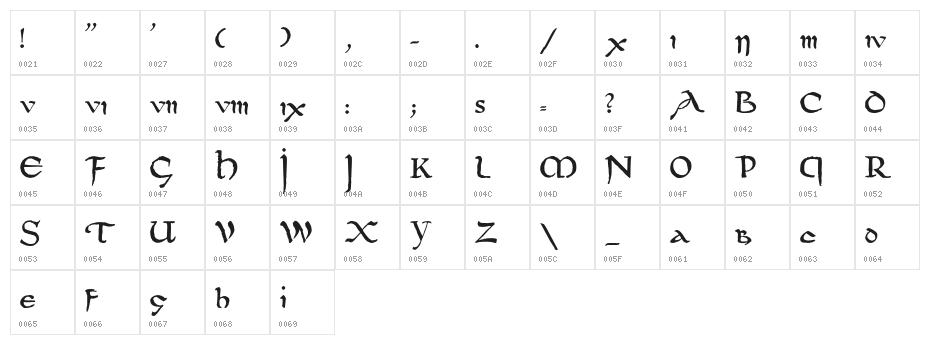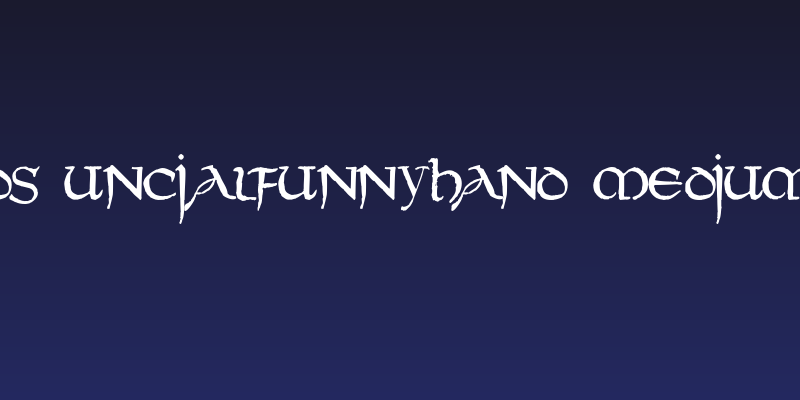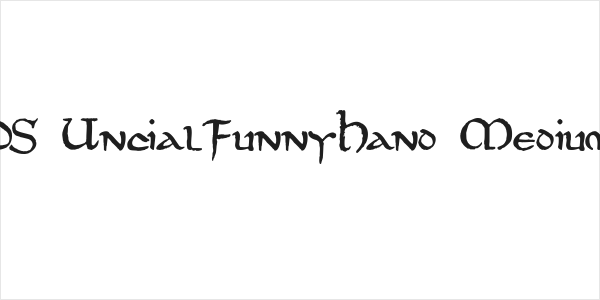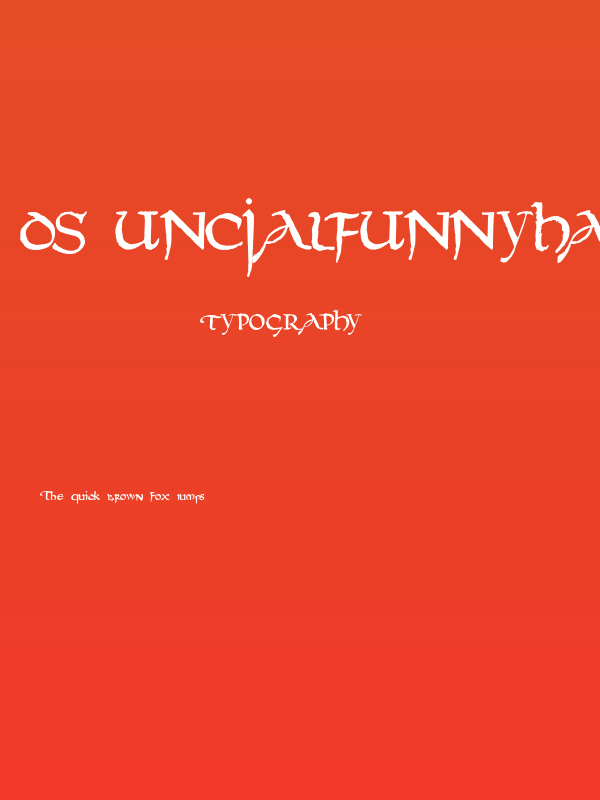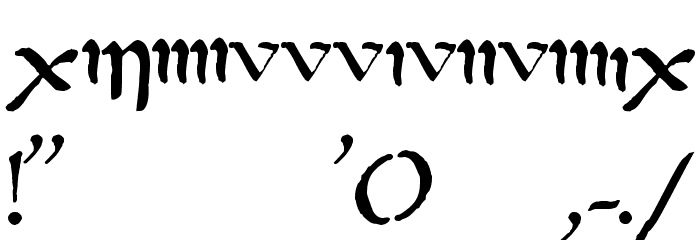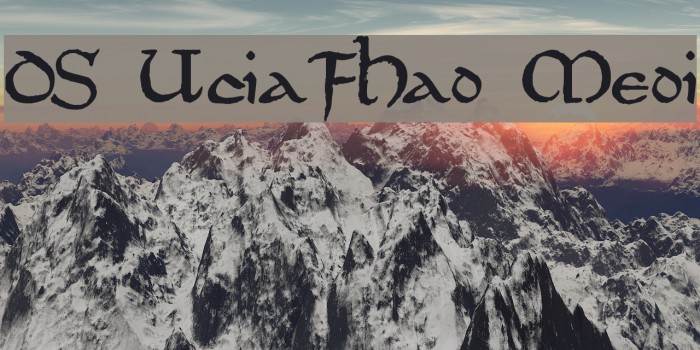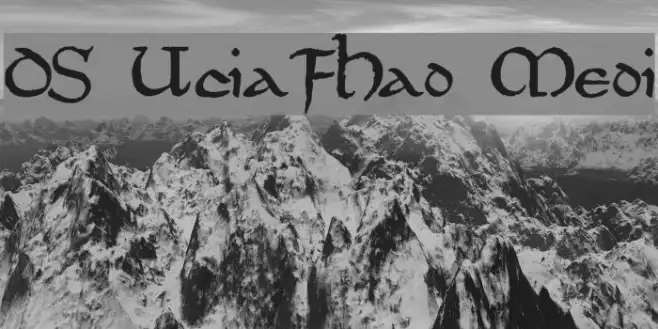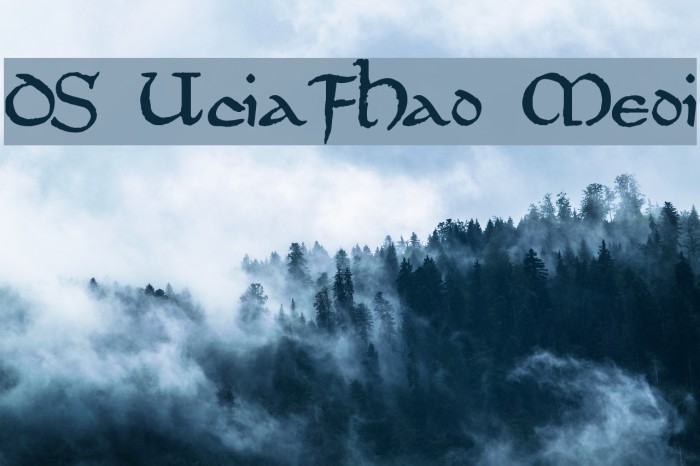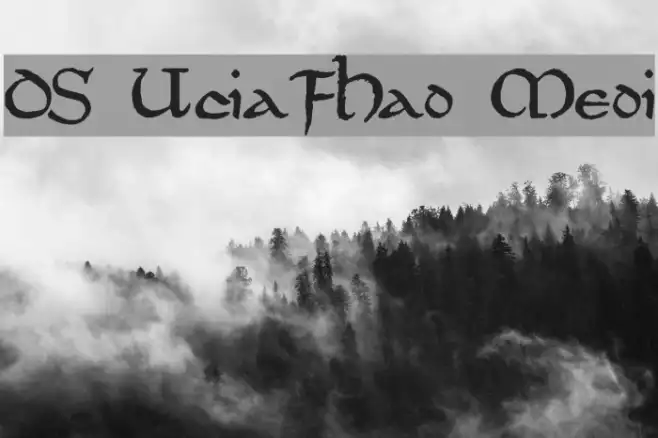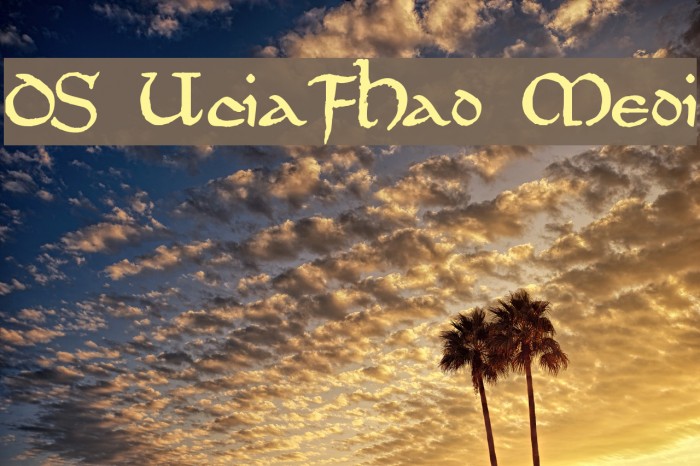
DS UncialFunnyHand Medium Font
| Anwendungsfall | Headlines, Logos, Artistic projects |
| Vorgeschlagene Projekte | Ideal for fantasy book covers, historical themed events, artistic posters, and creative branding. |